Font spasi, atau font kosmik, adalah jenis font yang terinspirasi dari elemen-elemen luar angkasa. Font spasi sangat populer dengan bentuk geometris dan desainnya yang unik dan tidak konvensional, menyerupai teknologi masa depan. Penggunaan font spasi pun tidak hanya terbatas pada desain cetak, tapi juga sangat cocok digunakan dalam proyek-proyek desain digital, seperti desain web, desain game, presentasi, grafis media sosial, dan masih banyak lagi.
Dengan desain yang kreatif dan inovatif, font spasi dapat meningkatkan daya tarik visual dari sebuah proyek desain. Dan, dalam artikel ini, kami menyediakan 45 font spasi keren yang bisa Anda unduh dan gunakan secara gratis untuk mempercantik desain Anda. Yuk, simak daftarnya di bawah ini!
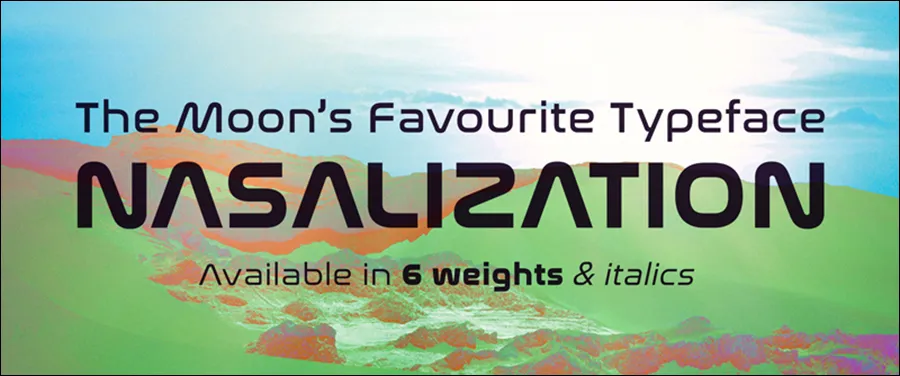
Font pertama adalah Nasalization. Font ini terinspirasi dari logo NASA pada tahun 1975, dengan desain yang halus dan modern. Cocok digunakan untuk desain-desain yang membutuhkan kesan futuristik dan kontemporer, seperti desain web atau poster.
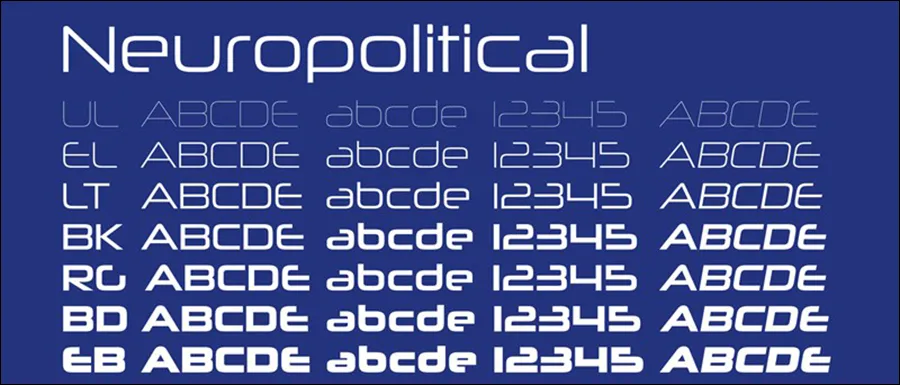
Font kedua adalah Neuropolitical. Karakter dalam font ini memiliki bentuk yang futuristik dan dinamis, dengan detail yang halus namun tetap terlihat jelas. Cocok digunakan untuk desain-desain yang ingin menyampaikan pesan modern atau teknologi, seperti logo perusahaan teknologi atau judul game, dan lain-lain.
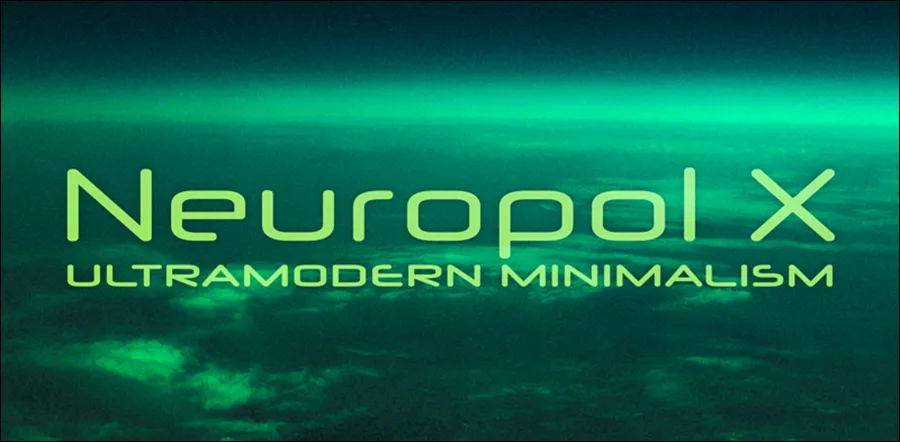
Selanjutnya adalah font Neuropol X. Font ini memiliki karakter yang terinspirasi dari teknologi canggih, dengan bentuk-bentuk yang dinamis dan modern. Cocok digunakan untuk desain-desain yang membutuhkan kesan futuristik dan energik, seperti dalam pembuatan poster atau grafis untuk media sosial.
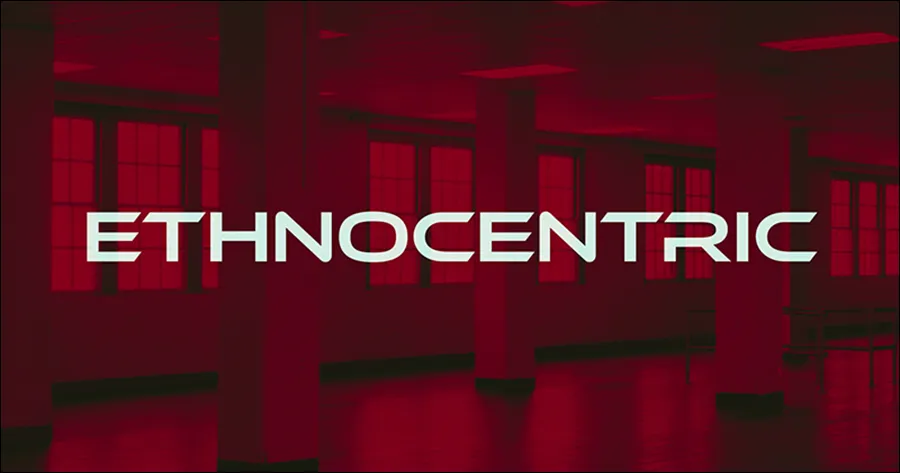
Font ini memiliki garis diagonal yang tajam dengan sentuhan etnis yang khas, namun tetap terlihat modern dan legible. Cocok digunakan untuk desain-desain branding atau papan informasi.
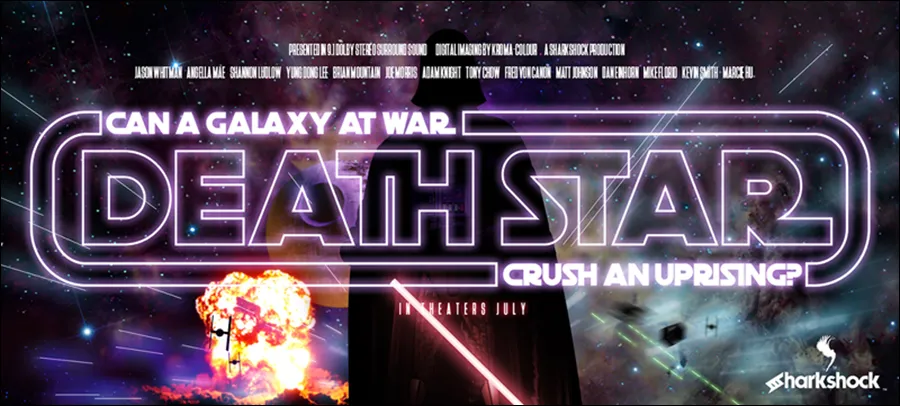
Font ini terinspirasi dari karakteristik Death Star dalam Star Wars, dengan bentuk fisik yang massif dan kuat. Cocok digunakan untuk judul-judul yang ingin menampilkan kesan epik dan dramatis, seperti pada poster film atau cover buku fiksi.
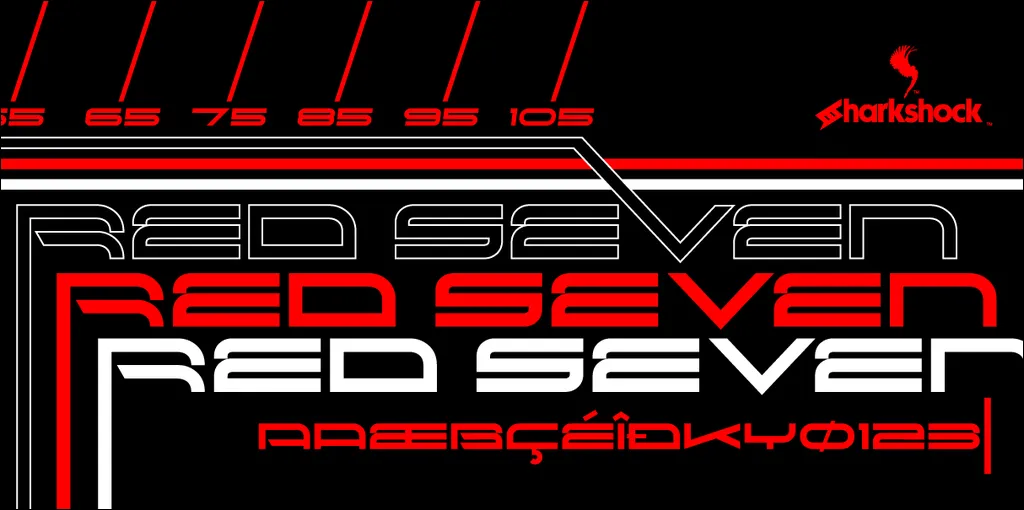
Red Seven memberikan kesan yang agresif dan kuat dengan bentuk fisik yang tegas dan berani. Cocok digunakan untuk desain yang ingin menonjolkan kesan dinamis dan penuh energi, seperti pada logo olahraga atau desain merchandise.
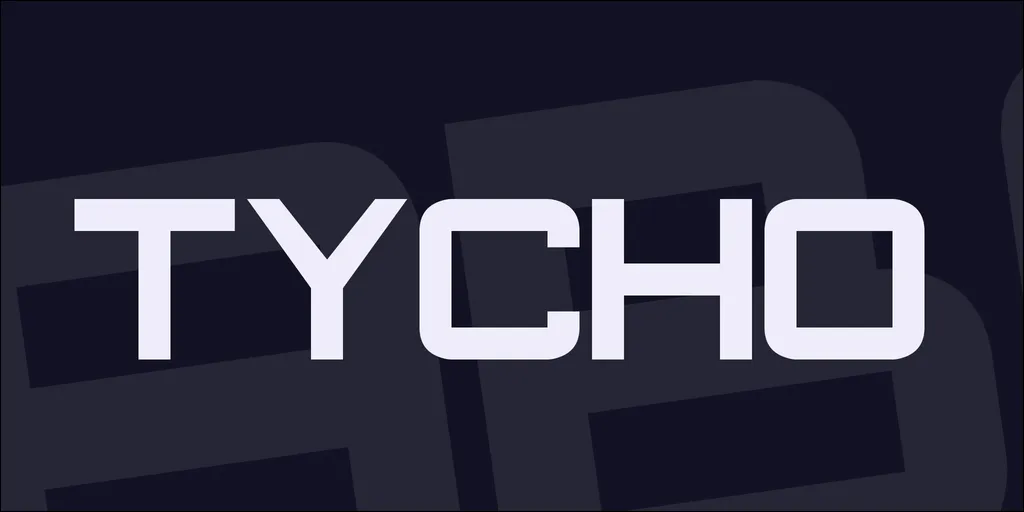
Font sans-serif ini memiliki bentuk techno yang bersih dengan sedikit sentuhan futuristik. Cocok digunakan untuk desain yang ingin menampilkan kesan minimalis namun tetap stylish, seperti pada desain layout majalah atau branding perusahaan.
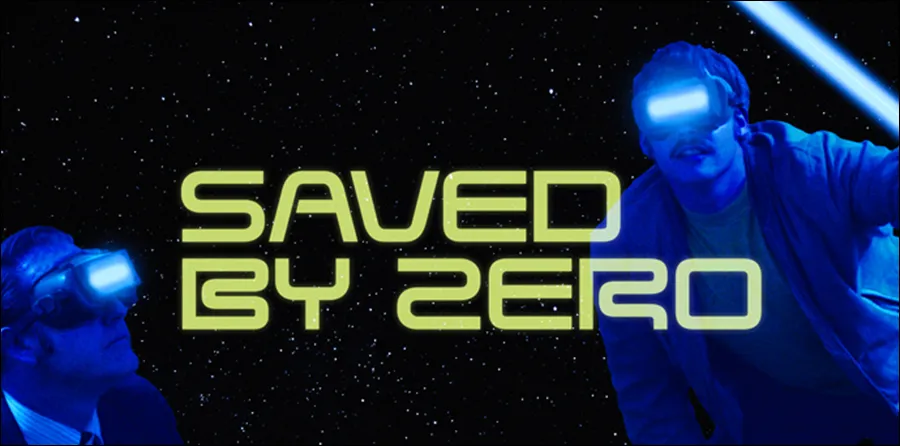
Saved by Zero memiliki desain retro dengan garis-garis yang elegan. Cocok digunakan untuk desain yang ingin menampilkan kesan yang klasik modern, seperti pada desain website atau poster acara.
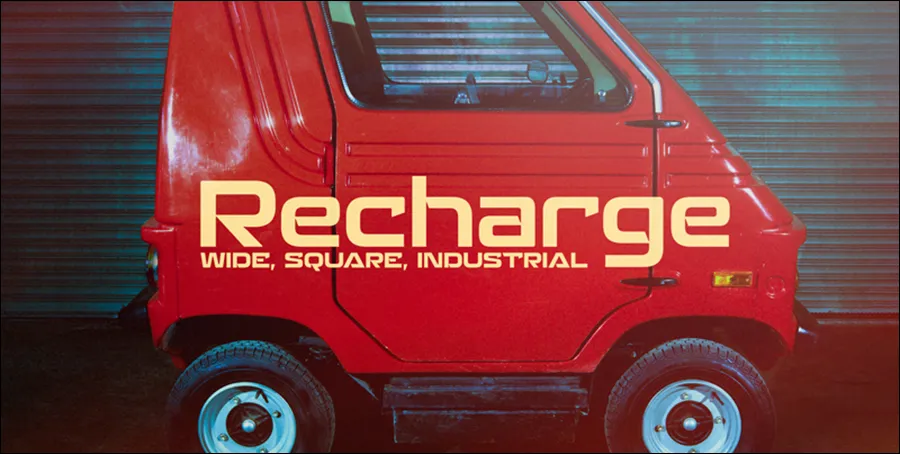
Recharge menampilkan desain persegi yang lebar dan modern, dengan detail yang halus dan mengalir. Cocok digunakan untuk desain-desain pembuatan poster atau cover album musik.
Dengan desain yang lebar dan garis kurva mekanis, font ini memberikan kesan yang solid dan tegas. Cocok digunakan untuk desain logo perusahaan atau branding produk.
Venite Adoremus memiliki desain futuristik dengan garis-garis lebar yang bersih. Cocok digunakan untuk desain branding, periklanan, dan desain lainnya.
Font ini memiliki kesan retro futuristik dengan gaya timeless. Cocok digunakan untuk desain yang ingin menampilkan kesan yang high-tech dan inovatif, seperti pada desain game atau poster konser musik elektronik, dan lain-lain.
Sebagaimana namanya, font ini memiliki desain yang massif dan elegan. Cocok digunakan untuk desain yang ingin menampilkan kesan yang besar dan monumental, seperti pada banner acara atau spanduk publik.
Star Jedi terinspirasi dari karakter Star Wars, dengan karakter yang mengingatkan pada tulisan-tulisan dalam film tersebut. Cocok digunakan untuk desain-desain yang ingin menampilkan kesan yang terkait dengan franchise Star Wars, seperti dalam pembuatan fan art atau merchandise, poster film, dan lain-lain.
Font ini menampilkan desain yang agresif dan kuat dengan garis-garis yang tegas menyerupai sayap burung falkon. Cocok digunakan untuk desain yang ingin menonjolkan kesan yang ganas dan berani, seperti pada pembuatan logo atau t-shirt desain.
Meskipun prinsip dasar penggunaan font spasi sama, ada beberapa perbedaan dalam pengaturan dan tata letak antara desain cetak dan digital. Misalnya, dalam desain digital, perhatikan juga responsivitas dan kejelasan font pada berbagai perangkat, sedangkan dalam desain cetak, pastikan kualitas cetak tetap terjaga.